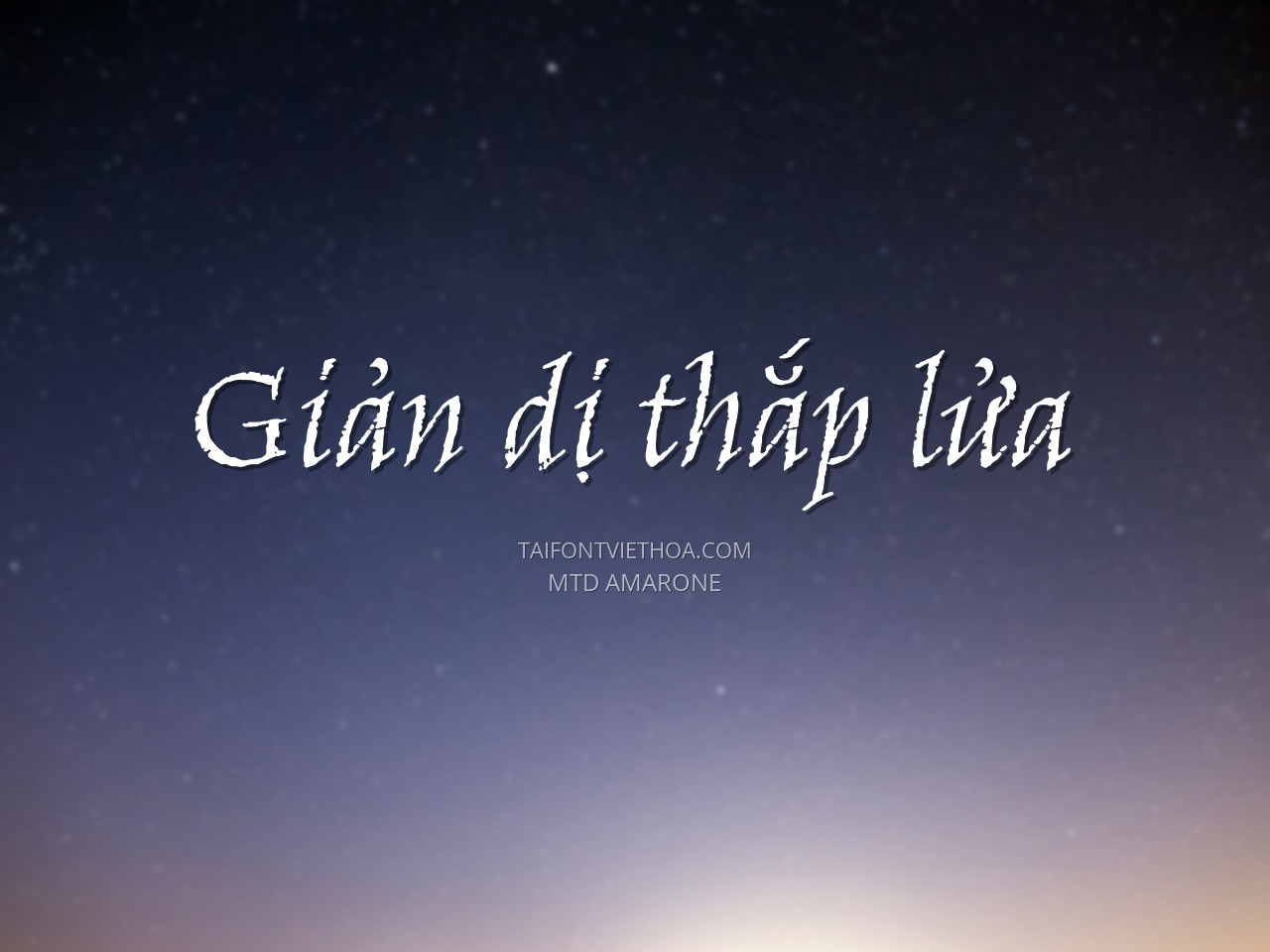
Font việt hóa MTD Amarone
Giới thiệu về font Amarone – Phong cách serif cổ điển kết hợp nét lãng mạn và sang trọng
Amarone là một kiểu chữ serif mang phong cách cổ điển pha chút lãng mạn, được thiết kế với những đường nét thanh thoát và tỷ lệ chữ hài hòa. Font lấy cảm hứng từ typography cổ điển châu Âu, thường thấy trên các bìa sách, nhãn rượu vang, bao bì cao cấp hay các ấn phẩm sang trọng. Amarone vừa mang tính truyền thống, vừa được tối ưu để sử dụng trong các thiết kế hiện đại, tạo nên sự cân bằng giữa hoài niệm và tinh tế.
Phiên bản Việt hóa do Mộc Hạthực hiện đã bổ sung đầy đủ dấu tiếng Việt, bảo toàn độ tương phản giữa nét thanh – nét đậm, và giữ nguyên tinh thần thiết kế cổ điển nguyên bản. Taifontviethoa.comđã lựa chọn và chia sẻ font Amarone như một giải pháp hoàn hảo cho các nhà thiết kế đang tìm kiếm một font serif mang đậm tính thẩm mỹ, phục vụ tốt cho các dự án yêu cầu sự sang trọng và lịch lãm bằng tiếng Việt.
Đặc điểm thiết kế thanh lịch và ứng dụng cao cấp của font Amarone
Font Amarone có các nét gãy gọn nhưng mềm mại, phần chân chữ sắc sảo và chi tiết tinh tế. Độ tương phản giữa các nét rõ ràng giúp font nổi bật ở kích thước lớn như tiêu đề, thương hiệu hay biển hiệu. Từng ký tự được trau chuốt để mang lại cảm giác cao cấp, cổ điển và chuyên nghiệp.
Amarone phù hợp cho các ứng dụng như: logo cao cấp, bao bì rượu vang, mỹ phẩm, nhãn sản phẩm thủ công, tạp chí thời trang, hoặc thiệp mời sự kiện sang trọng. Ngành nghề lý tưởng bao gồm: thời trang, ẩm thực cao cấp, xuất bản, mỹ phẩm, nội thất cao cấp và thương hiệu mang định vị truyền thống – đẳng cấp – nghệ thuật.